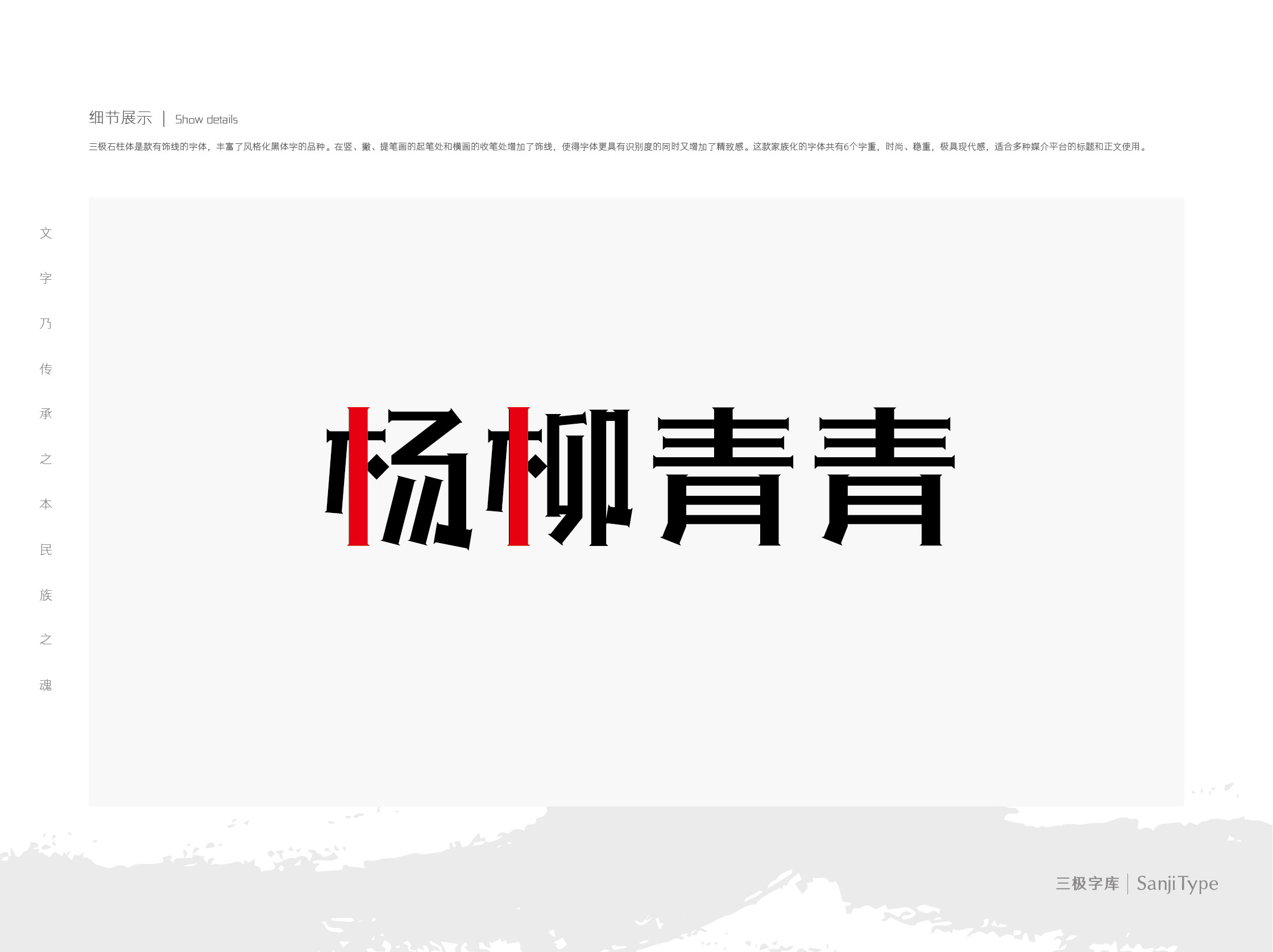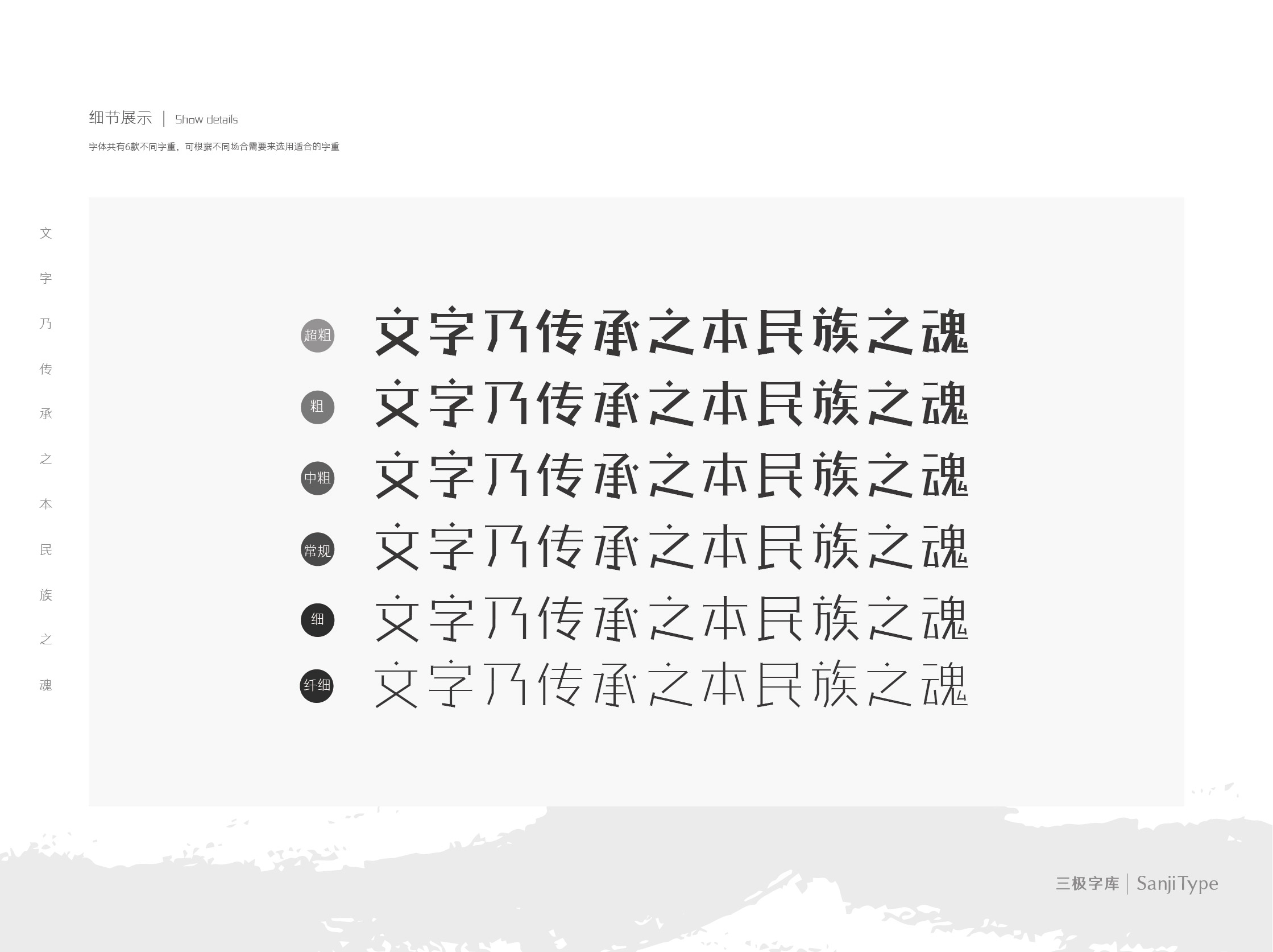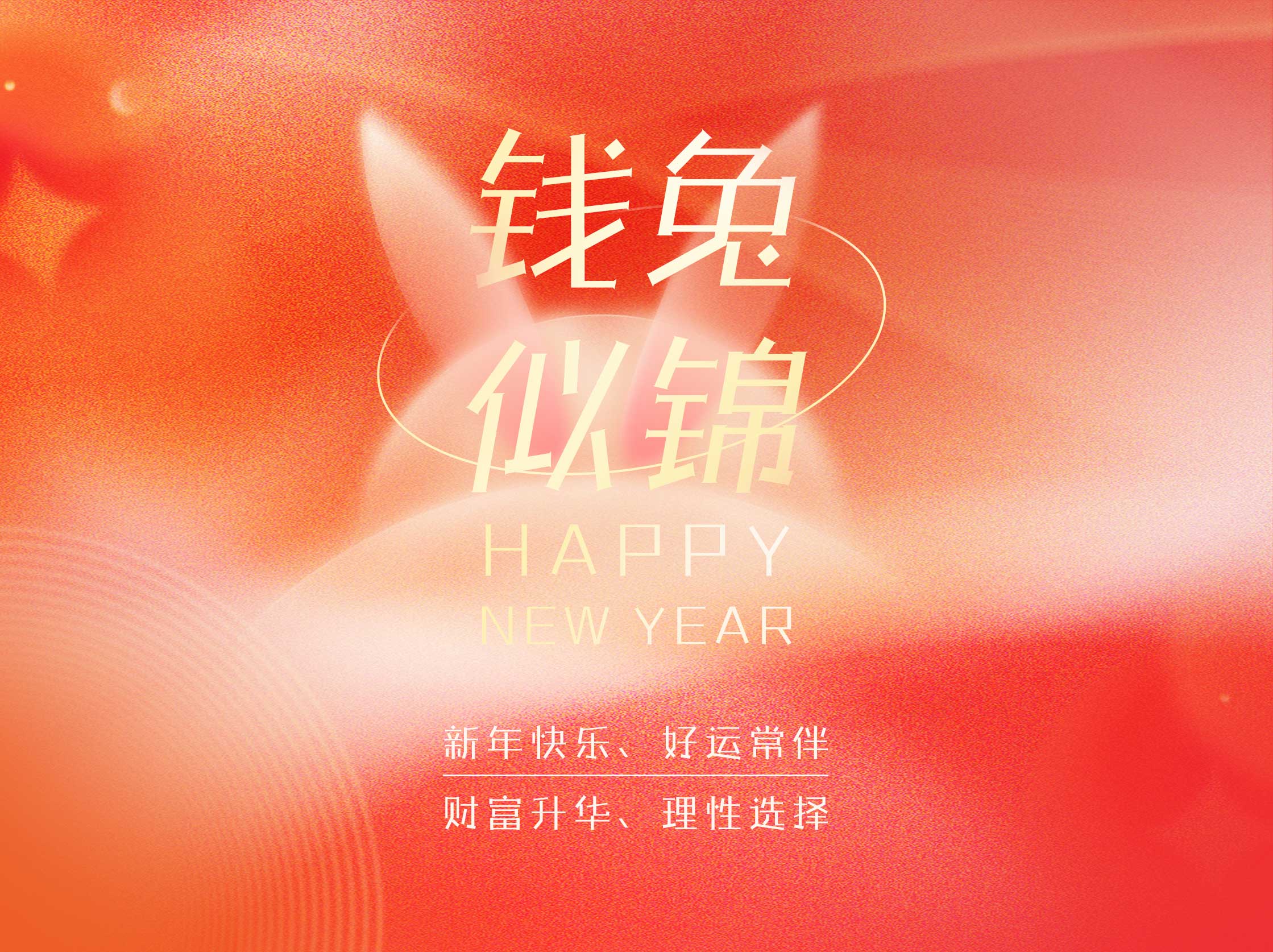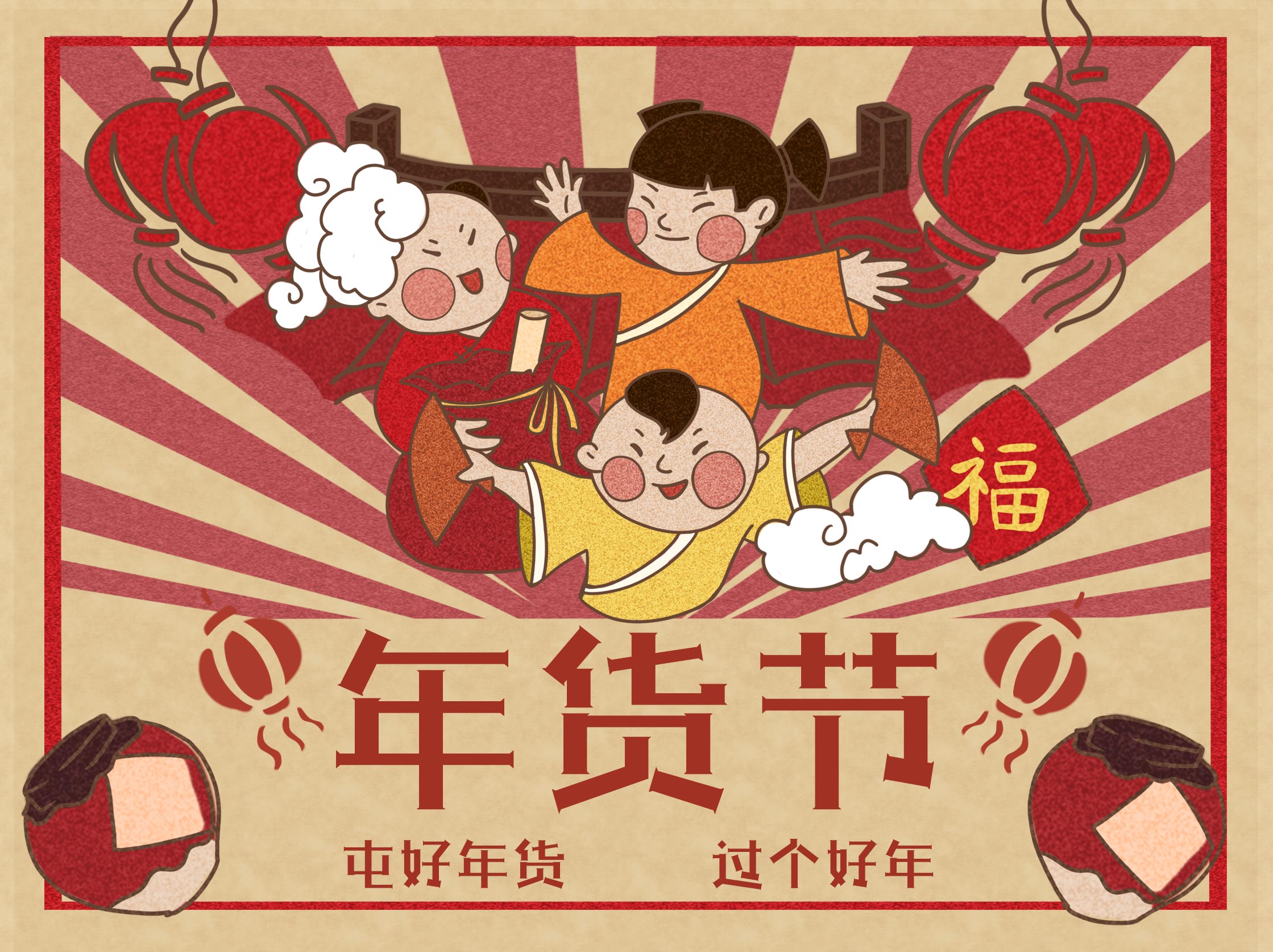
三极石柱体家族
三极石柱体 中粗
三极石柱体 细
三极石柱体 超粗
三极石柱体 粗
三极石柱体 纤细
三极石柱体
杜泽波
黑体
三极石柱体是款有饰线的字体,丰富了风格化黑体字的品种。在竖、撇、提笔画的起笔处和横画的收笔处增加了饰线,使得字体更具有识别度的同时又增加了精致感。这款家族化的字体共有6个字重,时尚、稳重,极具现代感,适合多种媒介平台的标题和正文使用。